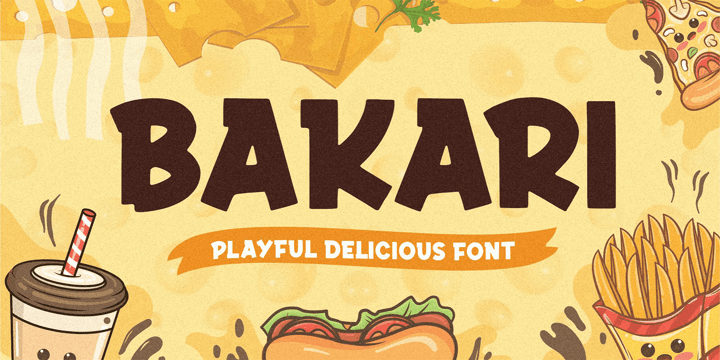
Myfonts Bakari Font
[Myfonts] Bakari Font
Привлекательный, смелый и игривый шрифт.
Этот шрифт производит очаровательное и сильное впечатление.
Bakari очень подходит для различных дизайнерских целей, таких как товары, упаковка, социальные сети, реклама, футболки, логотипы, мероприятия и многое другое.